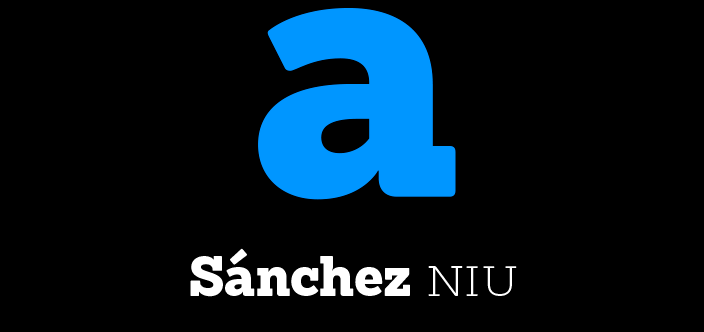
Sánchez Niu Font Family – Fonte Grátis
Sánchez Niu Font Family
A Sánchez Niu Font Family é uma nova família de serif slab que destaca-se por sua versatilidade e aprimoramentos, especialmente para textos longos. Introduzida pelo Latinotype, a família é um renascimento da famosa Sánchez, lançada originalmente em 2011 como o primeiro conjunto de fontes dessa casa editorial. Agora, com os ajustes nos proporções originais e a adição de novas caractereiras OpenType como minúsculas maiusculizadas, números antigos e alternativas estilísticas, Sánchez Niu oferece um design mais refinado para textos extensos. A nova versão da fonte continua mantendo seu estilo distintivo, com uma aparência natural que se adaptará perfeitamente tanto a headlines quanto aos logotipos. A família contém 720 caracteres, suportando 219 idiomas diferentes e é adequada para uso em web. A escolha da Sánchez Niu faz sentido não apenas pela sua utilidade em variadas aplicações de texto, mas também por seu aspecto sóbrio e elegante que se adaptará perfeitamente a qualquer projeto, tornando-a uma fonte popular entre designers digitais.